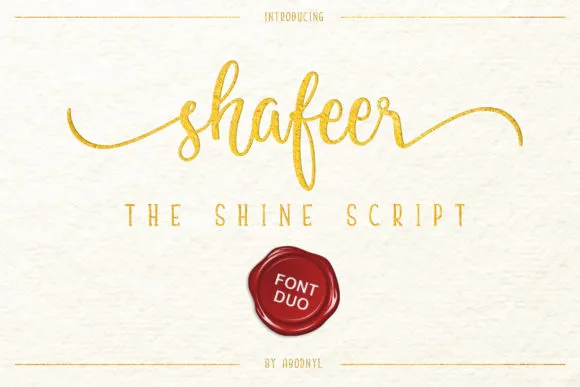
A Shafeer Duo é uma dupla de fontes que promete revolucionar seu trabalho de design. Ela traz consigo um estilo elegante e marcante, projetado para destacar qualquer projeto gráfico. Esta fonte perfeita para branding, convites de casamento, magazines, mugs, cartões de negócios, citações, outdoors e muito mais. Experimente a Shafeer Duo antes de comprar, certamente vai adorar como ela brilha em vários tipos de design. Engane-se se não estiver animado com o potencial desta dupla inovadora.